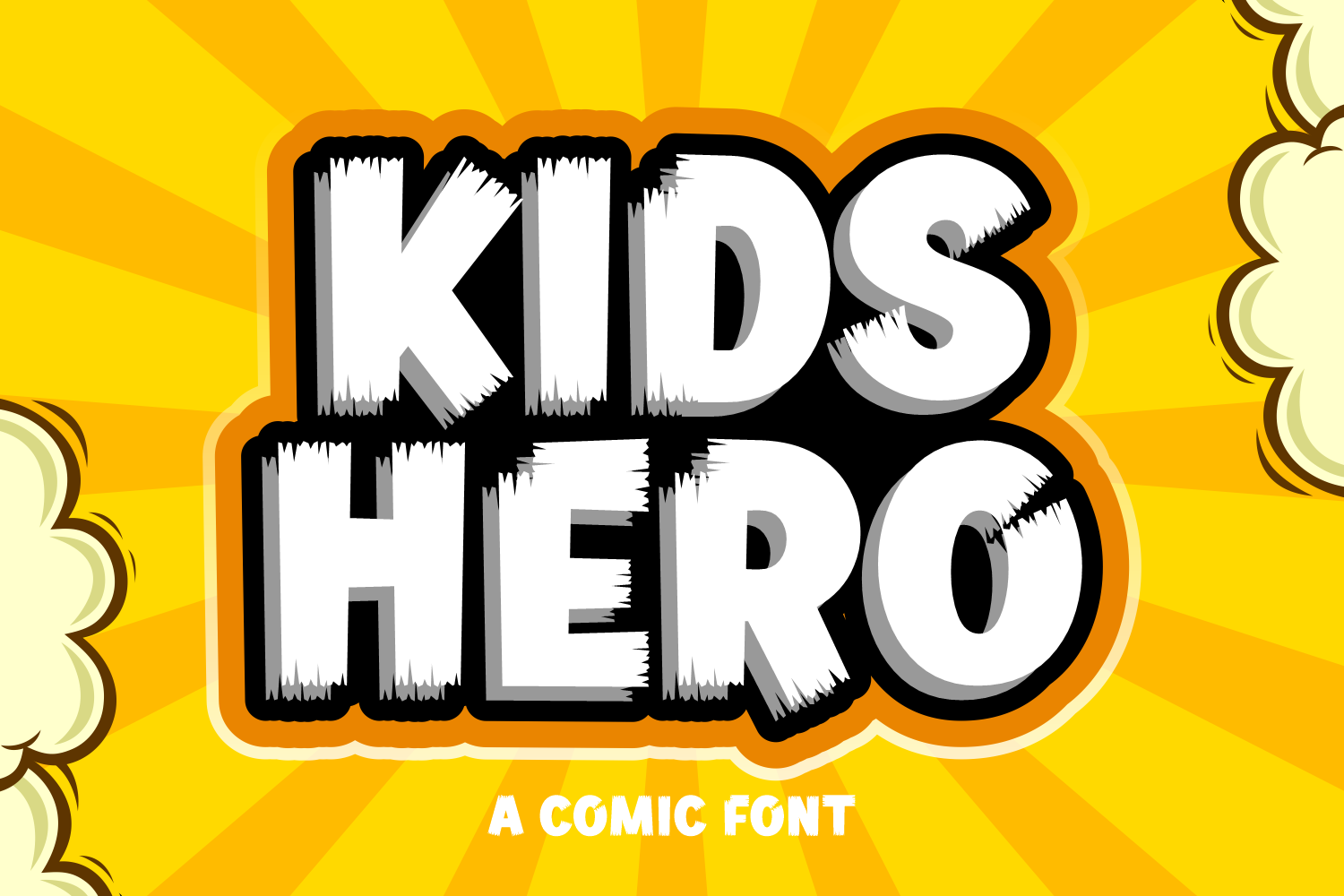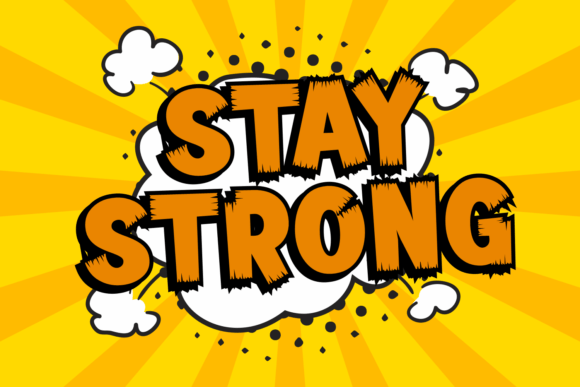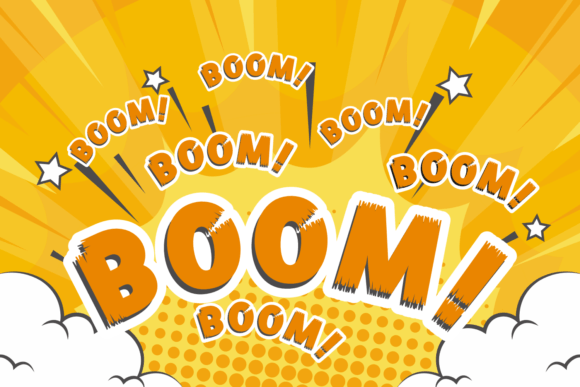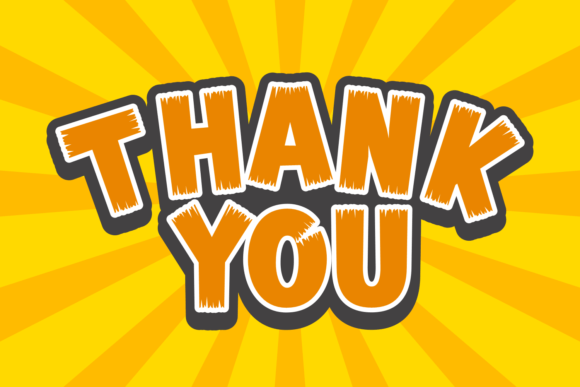
فونت Kids Hero انگلیسی
دانلود فونت Kids Hero انگلیسی Font کیدز هیرو |
| ⭐ مجموعه فونت | دانلود فونت انگلیسی قهرمان بچه ها Font Kids Hero |
| ⭐ توضیحات | Kids Hero یک فونت کمیک منحصر به فرد و چشمگیر است. این شخصیتهای سرگرمکننده و بازیگوش، حس شادی را به هر ایده طراحی که ممکن است داشته باشید اضافه میکنند. از آن برای ایجاد سرفصل های خاطره انگیز، جلد کتاب، عنوان، پوستر، بنر، تی شرت و موارد دیگر استفاده کنید! |